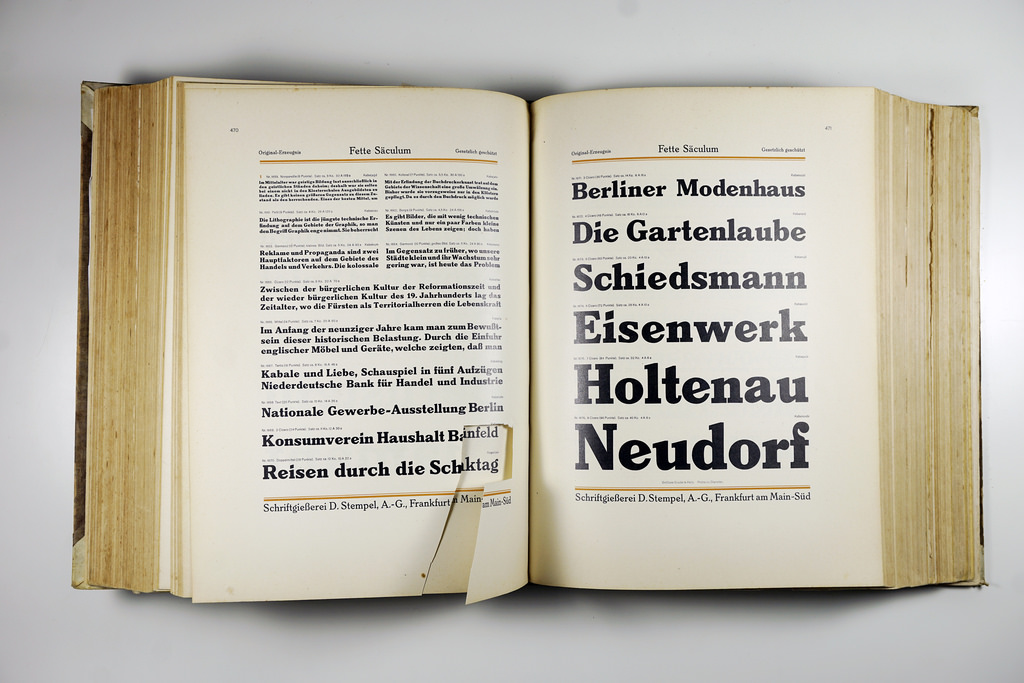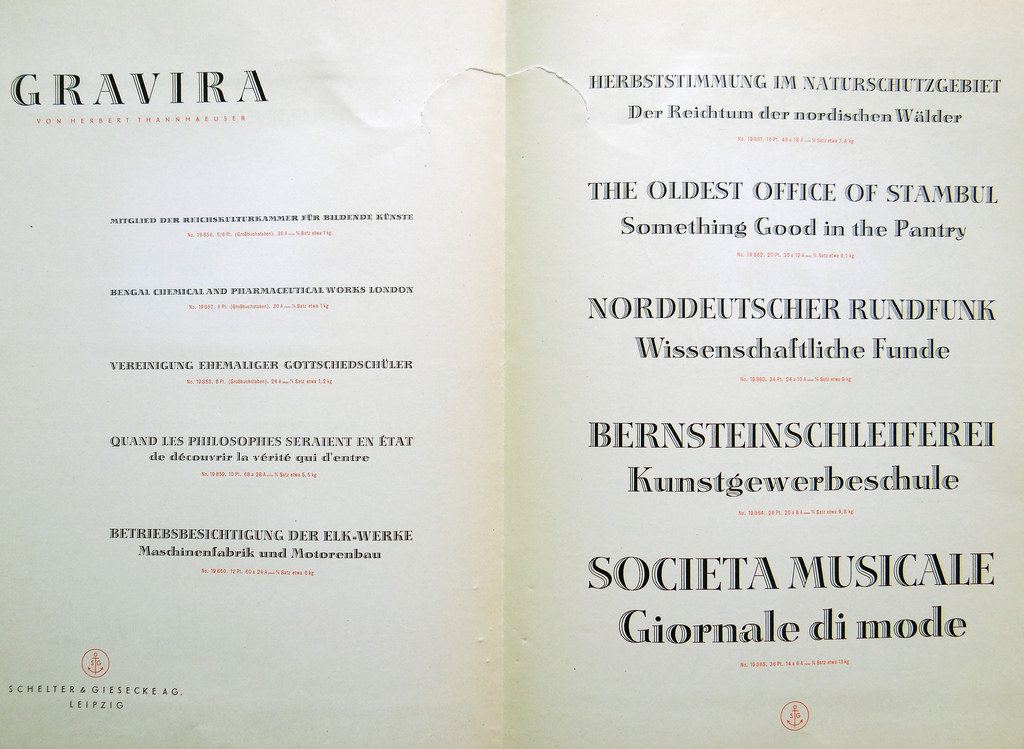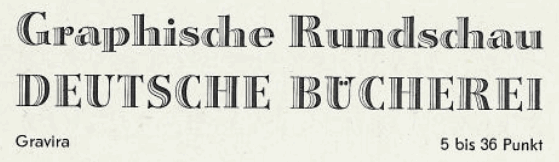
Ich bin neulich über den Namen "Säculum" gefallen. Eine Bleisatzschrift, die es wohl auch in kursiv sowie fett und mager gibt. Nirgends finde ich eine (verlässliche) Darstellung dieser Schrift. Hat jemand ein Schriftbild für mich?
Zudem würde mich interessieren, was die Schrift "Graviera" ist (habe neulich den Namen gehört, aber nichts gesehen).
vor einer Stunde schrieb PeterHamburg:
Zudem würde mich interessieren, was die Schrift "Graviera" ist
Ich kenne nur die Gravira von Herbert Thannhaeuser für Schelter & Giesecke, ca. 1935
Ich such mal ein Bild ...
Vielen herzlichen Dank RobertMichael! Das ist sehr hilfreich! Schön, die Gravira!!!
Am 11.11.2016 um 17:15 schrieb RobertMichael:
Auf die schnelle hätte ich das Bild ...
Fette Säculum D. Stempel